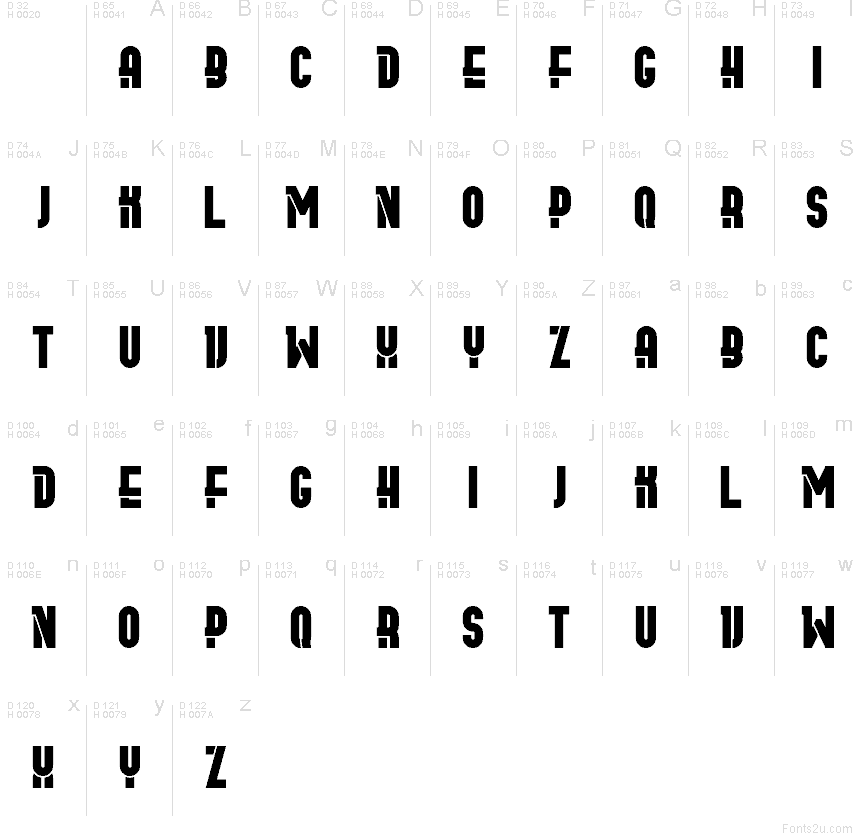
Ordinary Retro autorstwa Vladimira Nikolicia to darmowy krój retro typu display z dużymi, blokowymi literami i geometrycznym zacięciem, przypominającym szyldy z połowy ubiegłego wieku. Litery opierają się na ciężkich pionach, kanciastych łukach i wyraźnych wcięciach, co nadaje krojowi surowy, plakatowy rytm, zamiast gładkiego czy żartobliwego charakteru.
Świetnie pasuje do brandingu kawiarni w stylu vintage, okładek płyt, plakatów imprezowych, nagłówków czy opakowań, gdzie kilka słów musi oddać solidny, epokowy klimat. Jako darmowy font, sprawdzi się również w tytułach, monogramach i krótkich logotypach – dzięki zwężonym połączeniom i wyciętym rogom, nawet krótkie napisy wyglądają bardzo zdecydowanie.